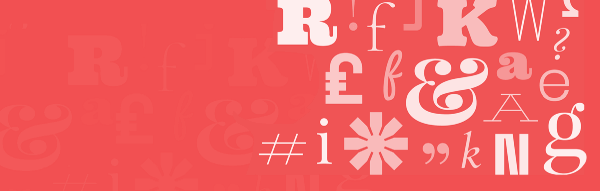
Google Fontsは素晴らしい無料のリソースです。 それぞれがどのような機能を持つのかを確認し、あなたのウェブサイトにぴったりなフォントを見つけてください。
Webフォントが話題になっているのは間違いありません。 何十年もの間、世界がデザイナーのやり方で物事を見るようになってきたようです。タイポグラフィが重要であり、フォントを正しく使うことが重要です。
あなたが大規模な組織の一員であれば、おそらくあなた自身のタイポグラフィを作成する余裕があるでしょう – 最近他の人も、自分専用のフォントを持っているようです。 Google Fontsのようなリソースは、あなたのブランドを確立し、コピーを提供し、そしてウェブサイトをスピードアップするための理想的な方法です。
フォントはなぜそれほど重要なのでしょうか?
Webサイトを設計するとき、デフォルトフォントを使用して他の重要な決定事項に集中する方が簡単な場合があります。 これは間違いではありません。しかし、あなたは、フォントの力と、フォントがウェブサイトにもたらす利点を見逃しているでしょう。 正しいフォントを選択すると、Webサイトに役立つことを表す例をいくつか示します。
フォントはブランディングに役立ちます
ウェブサイトに合ったフォントを選ぶことは、ブランドに大きな違いを生むことができます。 ロゴから数字、マイクロコピーまで、あなたのフォントの選択は読者との一種の非言語的コミュニケーションを確立します。 私たちの目が視覚的な合図に無意識に反応する方法のため(ストーリーテリングとUXについて詳しく書いています)、ウェブサイトのフォントは、ブランドに対する直接的な印象を、読者に与えます。
フォントを正しく設定すれば、ブランドの価値観や意図を正しく伝えることができます。 間違ったフォントを選択すると、自分のブランドについて何を言っているのか、自分自身が自分のブランドについて何を言っているのかが分からなくなる恐れがあります。
ロゴにCourierを使った高級ジュエリー会社を想像してみてください。 次に、すべてのWebコピーにLobsterを使用したヒップな新しい写真共有サービスを想像してください。 私たちの言っていることがわかりますね。
ブランドとコミュニケーションしたいものを考えてください – 贅沢で信頼できる、分厚くて正直な、または新鮮でクールなブランドですか? – そのメッセージを伝えるのに役立つフォントを選択してください。
フォントはUXにとって不可欠です
タイポグラフィは、UXデザインの最も重要な側面の1つです。 コピーやナビゲーションに間違ったフォントを選択すると、テキストが判読不能になり、Webサイトが使用できなくなる可能性があります。
私たちの同僚のスティーブンは、ウェブサイトに最適なフォントを選ぶとき、気を付けなければならない質問として、このリストをまとめました:
・フォントの太さはいくつですか?
・xの高さは読みやすさにさいてきですか?
・このフォントは複数のデバイスでうまく調整できますか?
・アクセス可能ですか?
・コントラスト比は?
選択したフォントが適切な太さを持ち、アクセシビリティ、X高さ、コントラスト比の基準を満たしていて、どのデバイスでも簡単に読むことができれば、おそらくそれは安全な策です。 覚えておいてください。知識豊富で非常に魅力的なデザイナーがそのフォントを好むというだけで、そのフォントがあなたのウェブサイトのにとって正しい選択であるということではありません。 フォントを決めたら、読者がフォントにどのように反応するかを確認するため、ユーザーテストを行う価値があります。
フォント、グロテスク、スラブの表示 – タイポグラフィの用語の説明
あらゆる技術分野が専門用語とタイポグラフィを共有していますが、簡単に言うと違いはありません。 フォントを調べるときに見る可能性がある、最も重要な用語の一覧とその意味は次のとおりです。
フォントの世界で最大の違いは、セリフフォントとサンセリフフォントの違いです。
セリフフォントは、その文字がセリフ、細い線、または文字の主要部分の終わりに付けられたストロークを特徴としているので、そのように呼ばれています。 セリフというはローマの石彫りに由来するもので、彫られる前に言葉が石の上に描かれていた方法に関連していると考えられています。 そのため、セリフ書体は「ローマン」と呼ばれることがあります。 GaramondとTimes New Romanは2つの古典的なセリフフォントです。
セリフの種類:古いスタイル、過渡的な、現代的なスラブ。
サンセリフフォントは、当然のことながら、セリフを使用しないフォントです。 これらのフォントは通常、よりシンプルでモダンに見え、19世紀後半から20世紀初頭の看板と広告の書体に基づいています。 セリフフォントとは対照的に、サンセリフフォントは「ゴシック」と呼ばれることがあります。 Helveticaは、おそらく最も有名なsans-serifフォントです。
サンセリフフォントの種類には、グロテスク、ネオグロテスク、幾何学、ヒューマニストなどがあります。
Googleフォントは、表示用またはテキスト用の目的によって分類されますが、2つのカテゴリの違いは何でしょうか?
テキストフォントは、Webサイトまたはアプリの本文で使用するように設計されており、小さいサイズでも見やすくなっています。 テキストフォントはきれいで、間隔が広く、表示フォントよりも分厚いので、小さいサイズでうまく機能します。
・一方、表示フォントは主にスタイリッシュでオリジナルのタイトルに見えるようにデザインされており、読みやすさはわずかに低下しており、本文での使用にはあまり適していません。
WebサイトでGoogleフォントを使用する利点
Google フォントは915個のフォントのコレクションで、すべてウェブサイトで無料で使用できます。 HTMLで使用したいフォントへの呼び出しだけで、使うことができます。
ウェブサイトでグーグルフォントを使うことの素晴らしい利点はここにあります:
・無料であなたのウェブサイトの見栄えを良くする
Google フォントを使用すると、ほぼ1000種類の見栄えの良いフォントに無料でアクセスでき、プロレベルの書体を自由に選択できます。 ほんの数年前だったら、同等の選択は数千ドルの費用がかかった可能性があります。
・プラットフォーム間の一貫性を高める
現在のウェブブラウザの大多数がGoogle フォントをサポートしているという事実のおかげで、Google Chrome、Apple Safari、Mozilla Firefox、Opera、Internet Explorerなどで使用できます。
・あなたのサイト、そしてインターネットをスピードアップ
WebサイトでGoogle Fontsを使用すると、サイトの見栄えをよくし、パフォーマンスを向上させることができます。 方法を説明しているグーグルから、このビデオをチェックしてください。
あなたのウェブサイトに最適な15のGoogleフォント
Lato
ワルシャワを拠点に活動するデザイナー、ウカシュ・ジエジッチは、Latoを作成し、本文テキストで透明に作業し、より大きなサイズのタイトルでの使用を際立たせました。 このサンセリフ書体ファミリーは普段慣れ親しんでいるものとは異なります。特に、フォントの詳細の一部が四捨五入されている点が異なります。
Merriweather
Eben SorkinのMerriweatherは、画面上で読みやすくなるように設計されています。 Merriweatherの大きいxの高さはフォントの読みやすさを高め、見出しやタイトルだけでなく長いテキストでの使用にも適しています。 Merriweatherには現在8つのスタイルがあります。ライト、レギュラー、ボールド、ブラック、ライトイタリック、イタリック、ボールドイタリック、ブラックイタリックです。
Montserrat
2011年にKickstarterプロジェクトから設立されたMontserratは、「20世紀前半に登場した都市のタイポグラフィの美しさを救う」ことを目指しています。 この魅力的なサンセリフフォントファミリはJulieta Ulanovskyによって作成され、彼女が住んでいるブエノスアイレスのモントセラト近所にちなんで名付けられました。
モントセラトの背後にあるインスピレーションについて、Ulanovskyはこう書きました。「手紙を描くために、私は都市空間でのレタリングの例に頼ります。 選択された各例は、長さ、幅、高さの比率がそれぞれ異なるバリアントを生成し、それぞれモントセラトファミリーに追加されます。 古いタイポグラフィとキャノピーは、置き換えられると元に戻せません。」 結果として得られる書体は現代の古典的な、20世紀初頭のタイプセットの優雅さの最新版です。
Muli
Muliは、後期Vernon Adamsによって設計された、多用途でシンプルなsans-serifフォントです。 もともとは表示フォントとして使用するように設計されていましたが、そのスペースのおかげで、テキストフォントとしてもうまく機能することができます。 Webおよびモバイルアプリケーションに適したMuliは、1階建ての小文字の「a」を他のものよりも好奇心が強い相対的な希少性を身に着けています。
Nunito
もう1つのVernon Adamsの作成物であるNunitoは、表示フォントとして設計されたサンセリフフォントです。 8種類のウェイトが用意されているので、スマートでスタイリッシュなサンセリフの見出しが必要なときに使用することをお勧めします。
Open Sans
最も人気のあるGoogleフォントの1つであるOpen Sansは、あらゆるシナリオで使用するための、オープンで無料のsans-serifフォントです。 非常に用途が広く、シンプルで親切なデザインであるため、テキストフォントとしてこのリストの他のフォントとうまく結合することができます。 Open SansはSteve Mattesonによって作成され、印刷、Web、モバイルなどの用途に最適化されています。
Oswald
20世紀前半の「Alternate Gothic」書体ファミリーを書き直したVernon AdamsのOswaldフォントは、コンピューターやモバイル機器でのデジタル使用のために設計されています。 タイトルに使用したり、サイズ制限のあるスペースにポップする必要がある引用符を引き出します。
Poppins
Indian Type Foundryによって作成されたPoppinsは、テキストまたは表示コンテキストで使用するための魅力的な幾何学的なサンセリフフォントです。 また、私たちのリストの最初のフォントであり、ヒンディー語とサンスクリット語を含む150以上の言語で使われているDevanagariシステムをサポートしています。
Roboto
Googleの社内Robotoは、Google Fonts Webサイトで最もダウンロードされているフォントであり、その理由を理解するのは難しくありません。 清潔、スタイリッシュ、スマートでありながら同時にプロフェッショナルでフレンドリーであるRobotoは、AndroidおよびChrome OSのデフォルトのフォントであり、GoogleのMaterial Designシステムで選択されているフォントです。 Robotoは、Webおよびモバイルでの使用に適した、シンプルで読みやすいものです。
ROKKITT
まったく異なるタイプについては、Rokkittを見てください。 Vernon Adamsによって設計されたRokkittは、19世紀半ば頃からのいわゆる「エジプト」の幾何学的スラブセリフフォントに触発されました。 表示目的のためにはっきりと意図されていますが、テキストとしても使用できます。
Rubik
Rubikは、Hubert FischerのPhilipp HubertとSebastian Fischerによって設計されたsans serifフォントで、Meir Sadanによって改訂および維持されたヘブライ語バリアントが含まれています。 ルービックの丸みを帯びた角はそれを快適でフレンドリーな感じにしてくれます。 それは完全に自宅でディスプレイやテキストとして使用できます。
Source Sans Pro
Paul D. Huntによって設計されたSource Sans Proは、Adobeの最初のオープンソース書体ファミリです。実際にはユーザーインターフェイス要素での使用を目的としたサンセリフ書体ですが、通常よりも幅が広いため、長いテキストにも適しています。
Spectral
Spectralは、GoogleのDocsおよびSlides Webアプリケーションでの使用を委託されたセリフ書体です。 エレガントでモダン、そして美しいスペクトラルは、本文と同様にタイトルと引用符で囲まれています。 最良の結果を得るためには、Open Sansのようなサンセリフフォントと組み合わせてください。
Work Sans
Wei Huangによって設計されたWork Sansは、20世紀初頭のグロテスク(すべてのサンセリフフォントのインスピレーション)に基づいています。 異なるウェイトはさまざまな用途に合わせて設計されています。標準ウェイトとミディアムウェイトはテキストの使用を目的としていますが、重いウェイトと軽いウェイトは表示目的によって最適化されています。
WebサイトでGoogleフォントを使用する
結論
Googleフォントはウェブサイトにとって、信じられないほど強力で多目的なリソースです。 900以上のフォントにアクセスできるようにすることで、GoogleフォントはWebサイトの見栄えを良くしながら、そのパフォーマンスを向上させ、インターネット全体の速度を向上させることができます。 さらに、Googleフォントはあなたのウェブサイトで簡単に始めることができます。